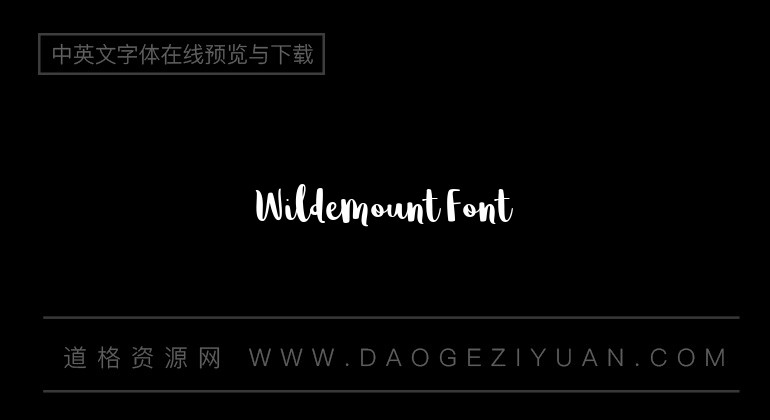
Wildemount Font是一种免费的手写字体,与Dungeons & Dragons的角色扮演游戏有关。它的设计灵感来自于Wildemount这个虚构的大陆,是D&D游戏的一个设定。 该字体拥有极具艺术感的手写风格,具有天然、粗犷、不规则的线条,让人感觉非常自然。它经常被用于D&D游戏的相关文档、海报、插图、标志等方面,以给人一种原始、神秘、冒险的感觉。 Wildemount Font可以在多个平台上免费下载和使用,包括Windows、Mac、Linux等。它是一个非常受欢迎的字体,尤其受到D&D玩家和爱好者的喜爱。内容介绍
Wildemount Font是一款非常不错的手写艺术字体,具有很好的视觉感,适合于文化类的宣传设计、商业类品牌的广告和产品包装设计以及个性化文字排版等较多场景。